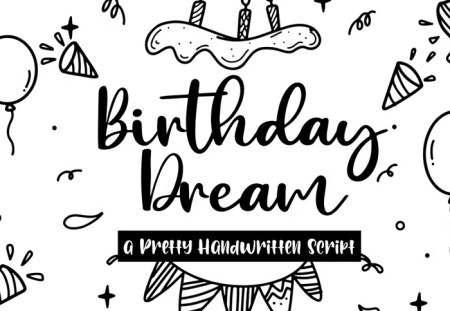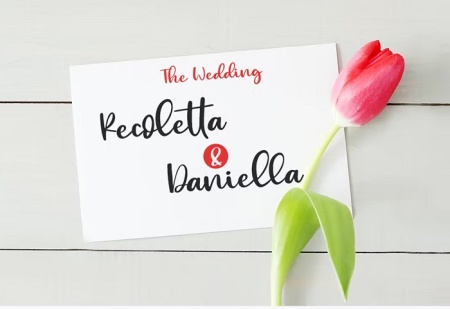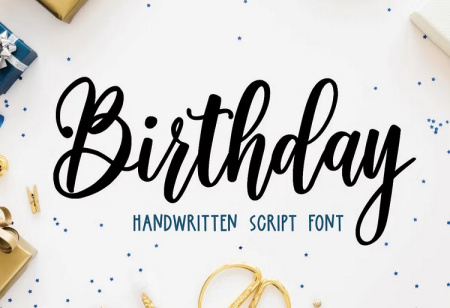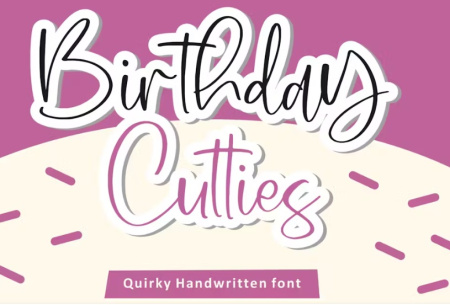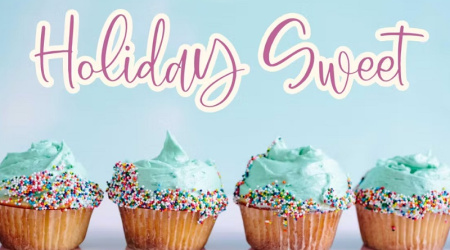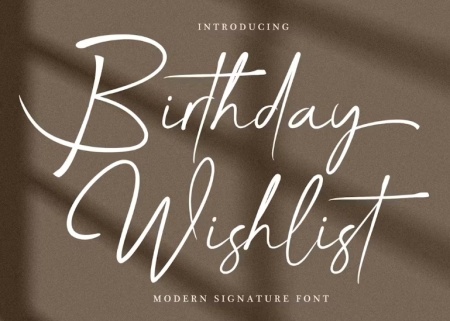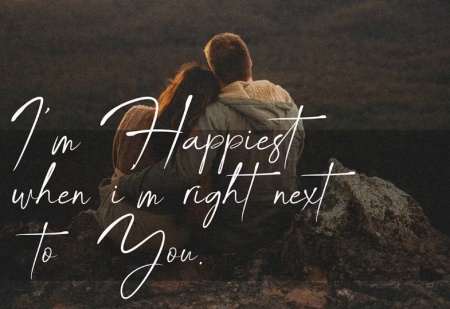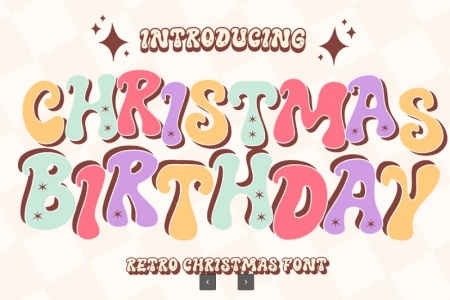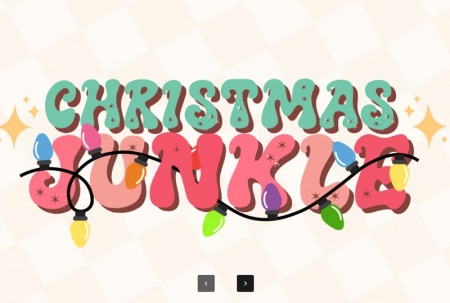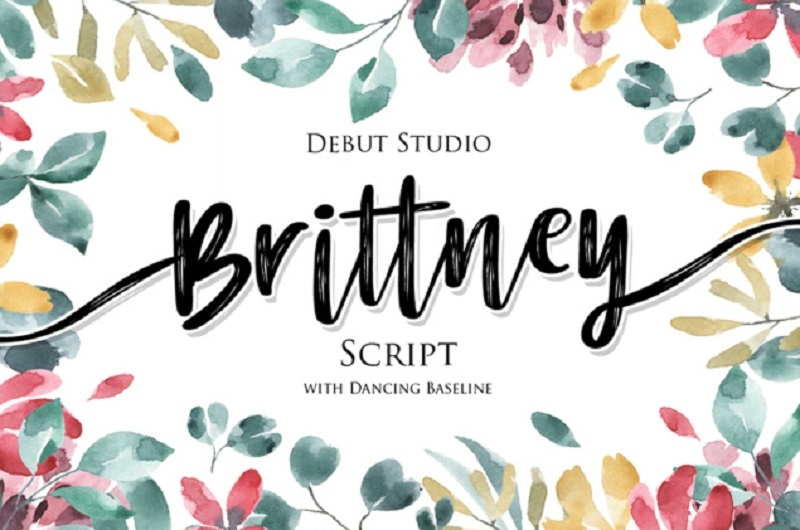
فونت انگلیسی تولد مبارک زیبا و خاص Happy birthday Font
فونت انگلیسی تولد مبارک یکی از بهترین راه ها برای ارسال پیام زیبا به عزیزانتان در روز تولدشان می باشد ! کاربردهای فونت انگلیسی تولدت مبارک بسیار زیاد می باشد و طراحان گرافیکی از این فونت انگلیسی برای استفاده در ساخت و ادیت کارت تبریک، بنر و پوستر جشن تولد استفاده می نمایند.در ادامه برای دیدن نمونه های این فونت و دانلود انواع فونت Happy birthday به همراه ویژگی های خاص آن همراه جی اف ایکس دانلود باشید.
فونت انگلیسی تولدت مبارک جدید Birthday Handwritten Font
اگر به دنبال دانلود انواع فونت Happy birthday تولد مبارک هستید این مطلب مناسب شما می باشد. این فونت دست نویس زیبا به صورت آپدیت به مجموعه اضافه شده است، شما می توانید برای طراحی های مختلف با موضوع تولد، عروسی، جلد کتاب، لوازم التحریر، بازاریابی، مجلات و سایر موضوعات دیگر از این فونت زیبا استفاده کنید. فونت تولد مبارک Happy birthday در 3 فرمت مختلف OTF، TTF و Webfont عرضه شده است که به راحتی می توانید از آن در سیستم عامل های Windows, Apple, Linux, Cricut, Silhouette استفاده نمایید.
فونت تولد مبارک به انگلیسی
اگر می خواهید به شیوه ای متفاوت تبریک تولد بگویید، می توانید از این فونت تولد مبارک به انگلیسی استفاده کنید. مناسب برای طراحی کارت دعوت تولد، کارت تبریک تولد، طراحی های گرافیکی و ... می باشد.
فونت تولد مبارک انگلیسی
اگر می خواهید به شیوه ای متفاوت تبریک تولد را طراحی کنید، این فونت تولدت مبارک به انگلیسی Birthday Wishlist را به شما پیشنهاد می کنیم. یک فونت زیبا مناسب برای طراحی کارت دعوت تولد، طراحی بنر، پوستر، شبکه های اجتماعی و ... می باشد.
دانلود فونت تولد به انگلیسی
Christmas Birthday نام یکی دیگر از فونت های تولد به انگلیسی است. این فونت با طراحی شاد، رنگارنگ و اغلب کودکانه، برای ایجاد فضای جشن و شادی در طراحیهای مرتبط با تولد به کار میروند. فونت تولدت مبارک مناسب برای طراحی کارت تبریک، پوسترهای تولد، ساخت گیف و انیمیشن و طراحی محصولات چاپی می باشد.
دانلود فونت انگلیسی فانتزی تولدت مبارک برای طراحی happy birthday
اگر برای طراحی کارت تبریک، پوستر، دعوت نامه، استوری یا طرح های گرافیکی تولد به دنبال یک فونت خاص هستید، مجموعه فونت انگلیسی فانتزی تولدت مبارک می تواند انتخاب مناسبی باشد. در این مجموعه از جی اف ایکس دانلود، فونت های انگلیسی با سبک های متنوع و جذاب برای طراحی عبارت **Happy Birthday** قرار گرفته اند که می توانید از آنها در پروژه های شخصی و تجاری استفاده کنید. این فونت ها برای ایجاد نوشته های متفاوت و چشمگیر در طرح های تولد، کارت تبریک، بنر و محتوای شبکه های اجتماعی کاربرد دارند و به شما کمک می کنند ظاهر نوشته «تولدت مبارک» را از حالت ساده و معمولی خارج کنید.
✅ شامل 6 فونت تولدت مبارک ✅ نام فونت انگلیسی1: Happy birthday ✅ نام فونت انگلیسی 2: Birthday Dream ✅ نام فونت انگلیسی 3: Birthday Cutties ✅ نام فونت انگلیسی 4: Birthday Wishlist ✅ نام فونت انگلیسی 5: Christmas Birthday